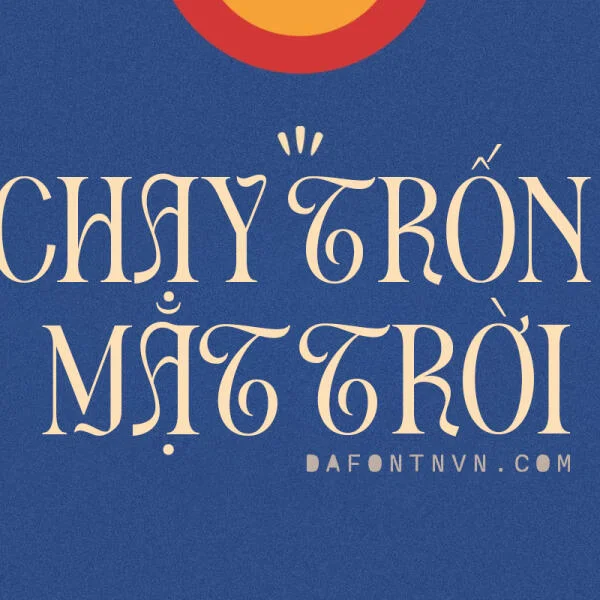
Download Font Grafika việt hóa - Modern Sans
Font Grafika - 1 font chữ được thiết kế hiện đại và tối giản trong mọi cài đặt.Tải về ở cuối bài viết.
Tổng quan về Font Grafika
Font việt hóa Grafika - Modern Sans một phông chữ hiện đại và các chữ ghép, chữ cái thay thế. Các nét đậm và nét mỏng được thiết kế ấn tượng mang đến cảm giác mạnh mẽ phù hợp với rất nhiều các thiết kế khác nhau như logo, tiêu đề, typography...
Chi tiết ký tự của Font Việt hóa Grafika